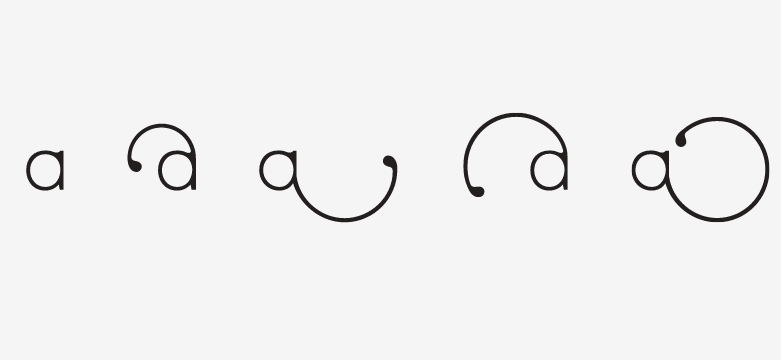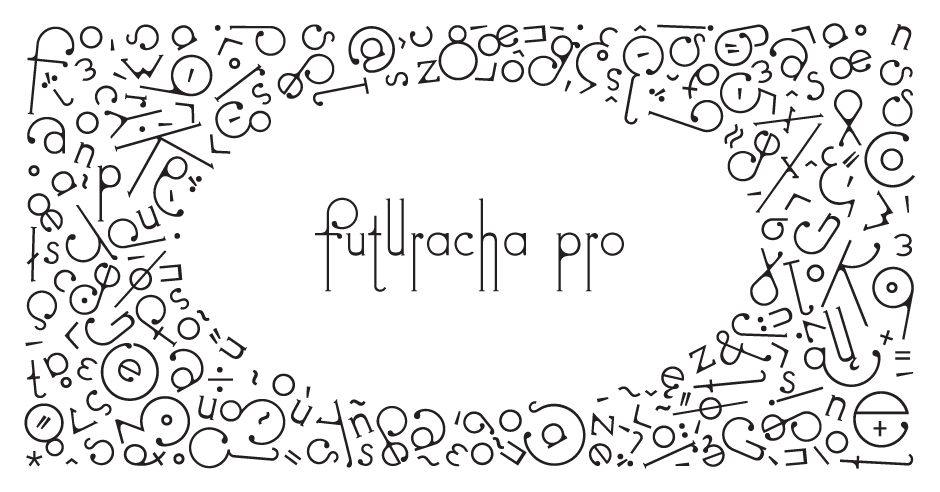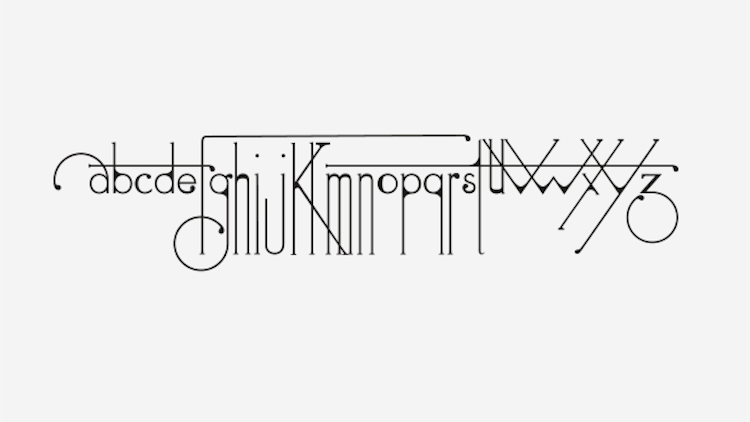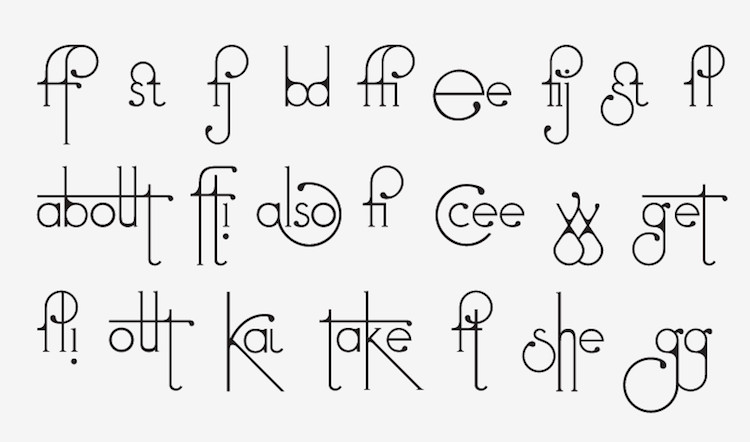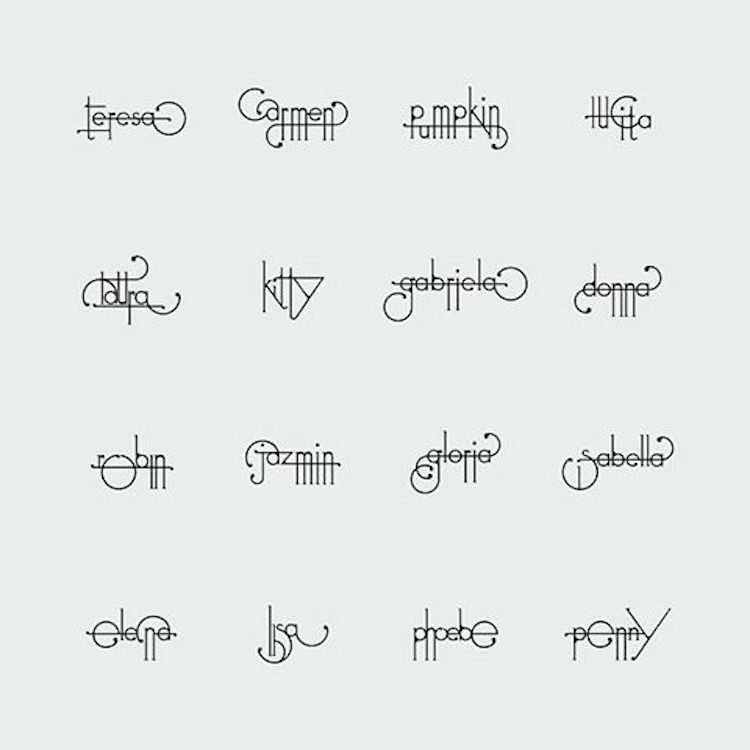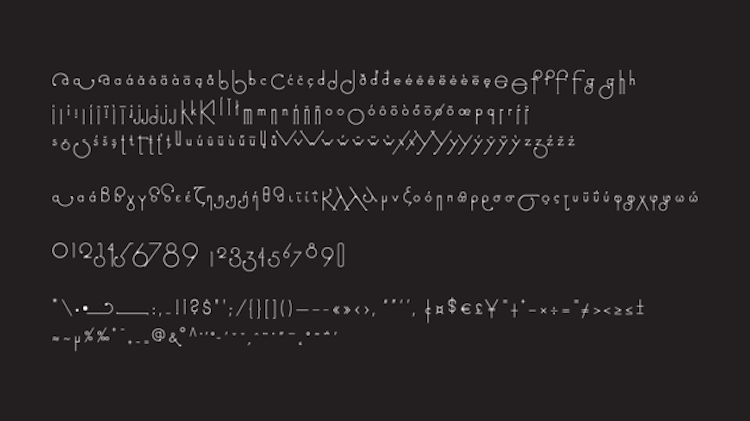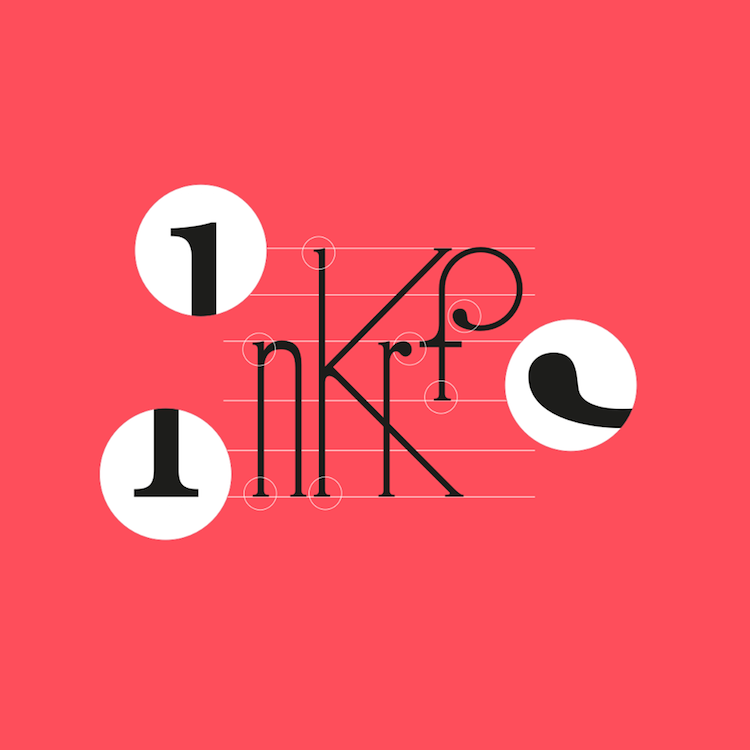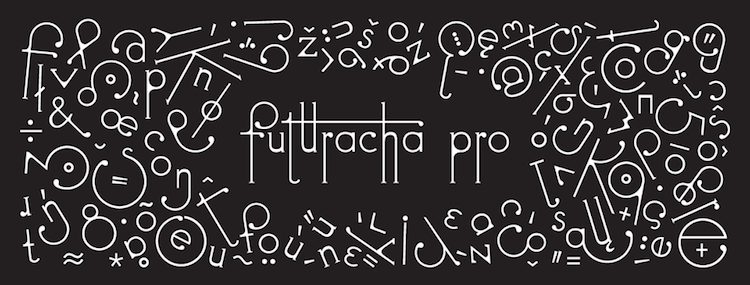
Es una nueva tipografía con letras estilizadas que cambian de forma a medida que escribimos.
El diseñador Odysseas Galinos Paparounis siempre mira hacia el futuro. Como fundador de Høly, una agencia formada por "exploradores interesados por el diseño", su innovador e imaginativo acercamiento a la tipografía es particularmente evidente en su nueva creación, Futuracha Pro, un tipo de letra que evoluciona ante nuestros ojos.
Futuracha Pro presenta espirales y curvas de estilo Art Nouveau contrastadas con remates sencillos. Aunque su estravagante aspecto es llamativo por si mismo, su diseño cobra realmente vida a medida que escribimos.
Según tecleamos con esta nueva fuente, las letras cambian de forma. Muchas se adornan con espirales adicionales, otras se vuelven alargadas y algunas simplemente permanecen iguales. Según Paparounis, estos complementos estilísticos están hechos enteramente pensando en el arte.
Su alfabeto ofrece letras únicas de estilo Art Nouveau.
"La mayoría de las fuentes aprovechan las ligaduras y adornos para realizar correcciones visuales", dice. "[Futuracha Pro] coloca la creatividad junto a la funcionalidad, el juego antes que la instrucción, la experimentación antes que los manuales".
En términos de sus influencias, Futuracha Pro es una fascinante fusión. Además de en la tipografía Futura, Paparounis buscó la inspiración en algo que nunca adivinaríamos: las cucarachas.
Como estudiante de diseño, se le pidió que ilustrara estos insectos domésticos. Mientras los observaba, su mirada se fijaba en sus antenas curvas y sus espinosas patas. Estas características inspiraron la estética orgánica de Futuracha Pro. Paparounis incluso nombró el tipo de letra pensando en estos animales, así "Futuracha" es una ocurrente combinación de "Futura" y "cucaracha".
Cada letra está compuesta de un conjunto de partes únicas y en evolución.